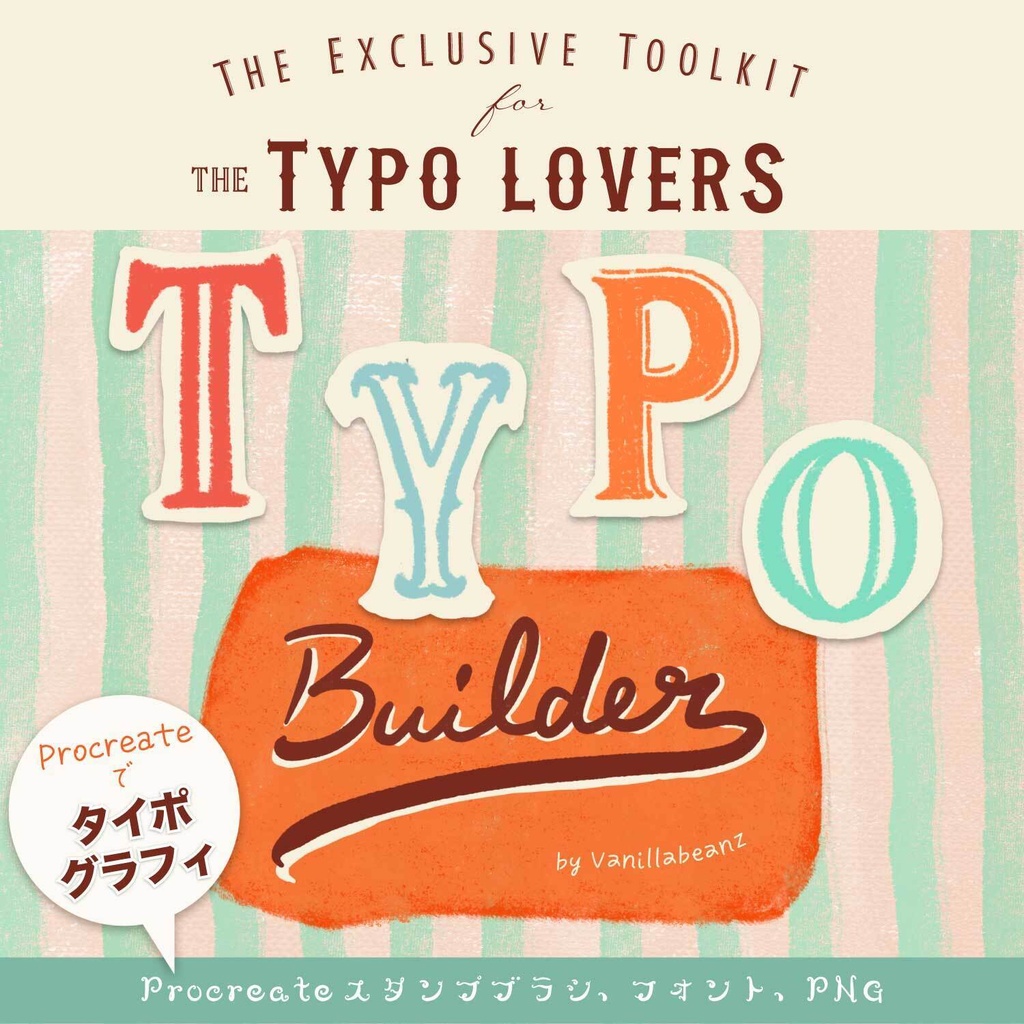
TYPO BUILDER | Procreateで簡単にタイポグラフィ - スタンプブラシ・フォント・PNG
Procreateがあればタイポグラフィできる! もちろんIllustratorやPhotoshopなど他のアプリでも使える! タイポラバーズに届け! TYPO BUILDER ~ タイポグラフィツールキット 文字を組むだけじゃない。遊ぶツール、それが TYPO BUILDER 文字を遊ぼう。デザインをもっと自由に。 「文字そのものをデザインしたい」 「手描き感のあるタイポをサクッと作りたい」 そんなクリエイターのためのタイポグラフィ専用ツールキットです。 【セット内容】 ・フォント(3種類) Wild West / Silhouette Sans / Elegant Echo ・Procreateスタンプブラシ(4種類) Wild West / Silhouette Sans / Elegant Echo / Template Box ・PNG素材(7点) Template Box ・TYPO BUILDER 使い方説明書(PDF) 【特徴】 ✔️Procreateにタップするだけでタイポが完成 ✔️ フォント付きだからテキスト入力も自由自在 ✔️ フォント・PNG素材はIllustrator・Photoshopなど他アプリでも活躍 Procreateだけで簡単にできる、オールインワンのタイポグラフィキットです。 SNS投稿のデザインや、オリジナル作品づくりに最適。 あなたのタイポグラフィがもっと楽しく、もっと自由に広がります。 【おすすめの使い方】 スタンプをベースにして、お気に入りのブラシを使って手描きでアレンジ! オリジナリティ溢れる作品に! ========================== TYPO Builderでつくる!オリジナルハロウィンカードを無料配布してます ダウンロードはこちら↓ https://vanillabeanz.booth.pm/items/7416929 ========================== オリジナルウェスタンハロウィンカードの作り方をnoteにて配信 note記事はこちら↓ https://note.com/vanillabeanz_jp/n/na30ca808631b ========================== 人生をタイポグラフィとともに! Life With Typography! 商用利用OKです。